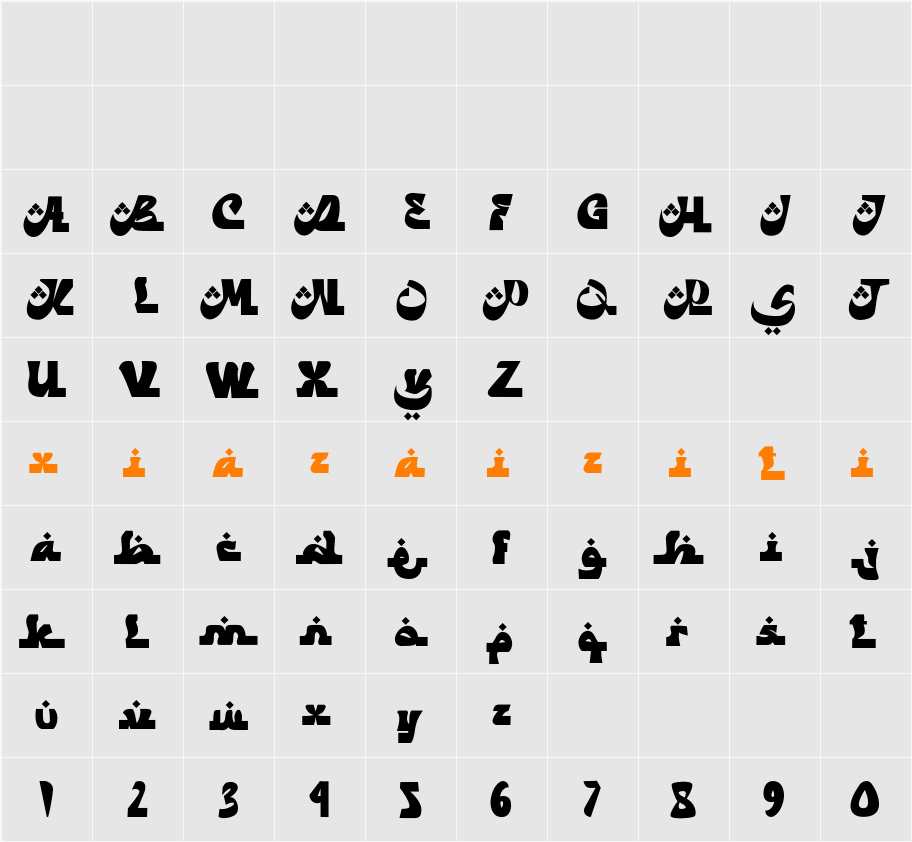
Yalla Arabic
Yalla Arabic,这款字体结构工整、笔画清晰,兼顾美观与易读性,适用于标题、正文、海报、包装、LOGO 等多种场景。字形优雅稳定,风格百搭耐看,适配日常排版与创意设计,让文字呈现更舒适、更具质感。Yalla Arabic一笔一画,皆是细节,以均衡的比例、流畅的线条打造舒适视觉体验,字形端正大气,风格简约现代。无论是商业设计、品牌宣传还是日常排版,都能轻松驾驭,让文字更有格调与力量。Yalla Arabic字体下载。